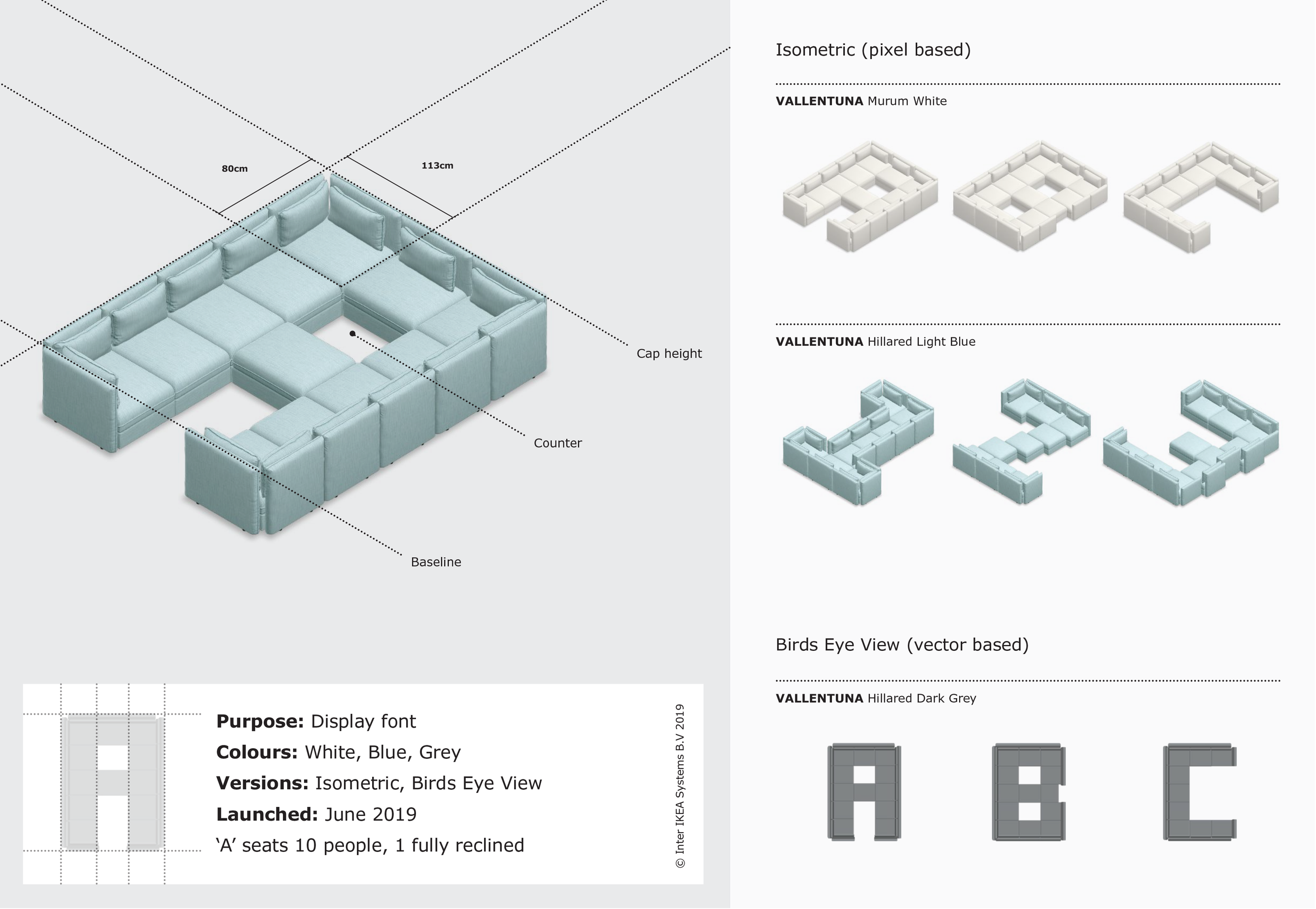
IKEA представила шрифт «Soffa Sans». Он самый комфортный в мире — потому что буквы сделаны из диванов!
Производитель мебели IKEA выпустил бесплатный шрифт «Soffa Sans». Все буквы в нем составлены из диванов «Валлентуна» белого, серого и голубого цветов. IKEA назвала свой шрифт «самым комфортным в мире». Скачать его можно здесь.
Создатели шрифта вдохновились недавним флешмобом в соцсетях, участники которого создавали крепости, лабиринты и другие (очень странные!) конструкции из диванов с помощью онлайн-планировщика помещений IKEA.
Идея создания «Soffa Sans» принадлежит британскому подразделению IKEA. Шрифт был разработан в сотрудничестве с digital-агентством Proximity London, пишет издание о рекламе, маркетинге и дизайне The Drum. Для создания букв использовались 1434 дивана «Валлентуна». Если бы кто-то решил воссоздать буквы «Soffa Sans» из реальных диванов, на их покупку ушло бы больше 134 тысяч долларов.